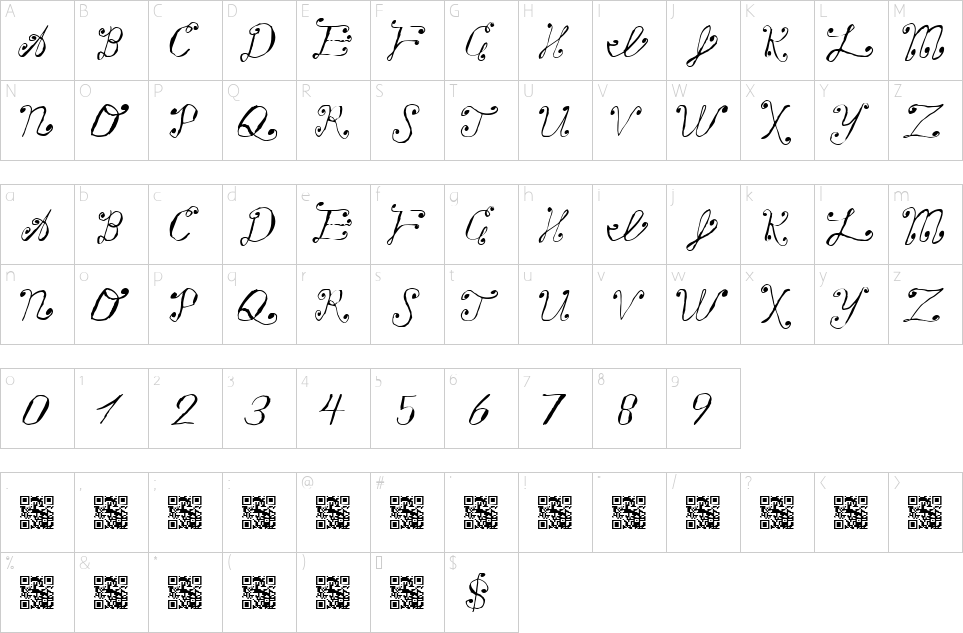
A fonte “Making A List Checking It Twice” é uma opção ótima para quem busca uma fonte com um tom alegre e divertido, ideal para adicionar um toque agradável a qualquer projeto de design. Desenvolvida pela JLH Fonts, essa fonte foi projetada para ajudar a tornar sua lista de compras ainda mais animada. Suas letras levemente curvadas e estilizadas fazem dela uma fonte divertida que vai aprimorar seu trabalho sem comprometer sua funcionalidade. Com sua simplicidade e seu design único, a fonte “Making A List Checking It Twice” pode ser usada em um grande número de projetos, desde listas de compras até cartões de aniversário. Atualmente disponível para download, ela já foi baixada mais de 3.154 vezes, evidenciando seu valor como fonte de graça. Se você está procurando por uma fonte divertida e criativa, “Making A List Checking It Twice” é uma escolha excelente.